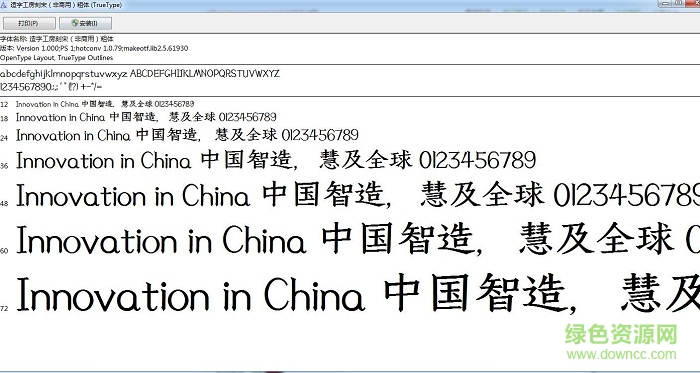
软件介绍 软件标签: 造字工房刻宋体 造字工房 mfkesong-bold字体又叫造字工房刻宋(非商用)粗体,是一款刚柔并济的宋体字体,蕴含传统字体特点,易辨易读,十分耐看,需要的朋友快来绿色资源网下载吧!宋体字体由来宋体是生而具来的印刷体,产生于雕版,成型于明朝。常用于书籍、杂志、报纸印刷的正文排版。宋体定义今天版本学家对于宋体字下的定义是:“横平竖直,横细竖粗,起落笔有棱有角,字形方正,笔画硬挺。”起落笔的棱角,应是宋体字的最大的特征!造字工房刻宋粗体安装方法方法一:控制面板/字体/文件/安装新字体;方法二:直接将字体复制到C:\WINDOWS\Fonts。方法三:针对win7系统,用户只需选中字体右键安装即可。 软件截图 上一张下一张(1 / 1) 安装详细截图 猜你喜欢 宋体字体 宋体字体 宋体是目前最常用的一款汉字字体,宋体成型于明朝,历史悠久,字体特点是横细竖粗,线条平直,结构严谨,工整又不失大气,非常适用于文字排版方面! 查看更多>> 原版宋体 5.37M/中文/1.4/下载 繁体宋体字体打包 14.64M/中文/2.5/免费版下载 经典中宋繁 regular 3.26M/中文/5.0/下载 粗标宋体 2.44M/中文/5.0/下载 方太梦想宋字体(中/细/粗体) 6.36M/中文/2.5/非商用下载 宋体-亮体(chinese-gb2312) 5.85M/中文/5.0/下载 其他版本下载 标题 大小 更新日期 下载 下载地址 电脑版 mfkesongnoncommercial-bold字体 ttf版 点击报错 软件无法下载或下载后无法使用,请点击报错,谢谢! 关闭报错反馈 请描述您所遇到的错误,我们将尽快予以修正,谢谢! *必填项,请输入内容 本类最新 dreamweaver字体库 首尔南山体字体 v1.06 官方版 潮字社风云简ttf 潮字社凌渡鲲鹏简体字体 潮字社曾玉波手书简字体 微博慧心字体 相关文章 第五人格摇曳的灯火怎么触发 第五人格灯火触发攻略 系统问答 System Idle Process是什么 Windows 7 RTM Build各版ISO详细介绍 如何解决Web服务器能Ping通但不能访问 彻底杜绝PHP的session cookie错误 ASP实例教程:FileSystemObject对象 用户评论 热门评论 最新评论 发表评论 查看所有评论(0) 昵称: 请不要评论无意义或脏话,我们所有评论会有人工审核. 字数: 0/500 (您的评论需要经过审核才能显示)